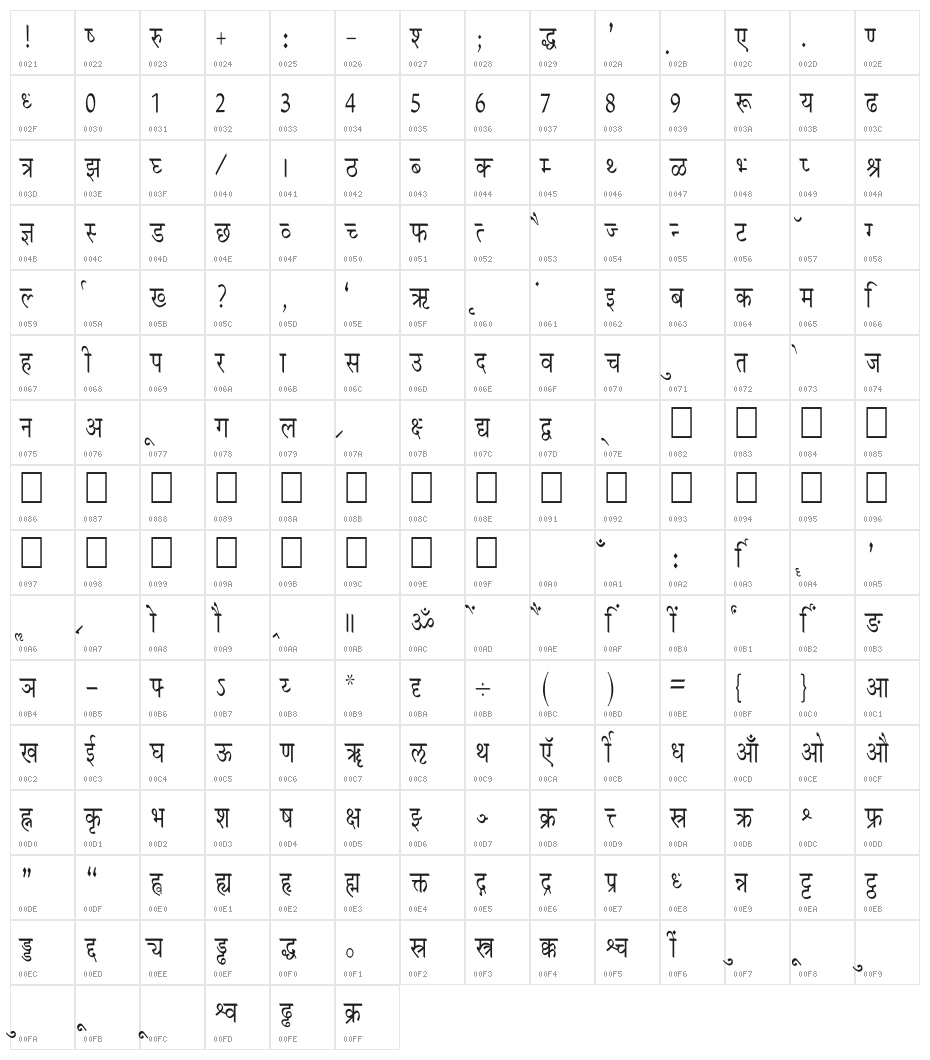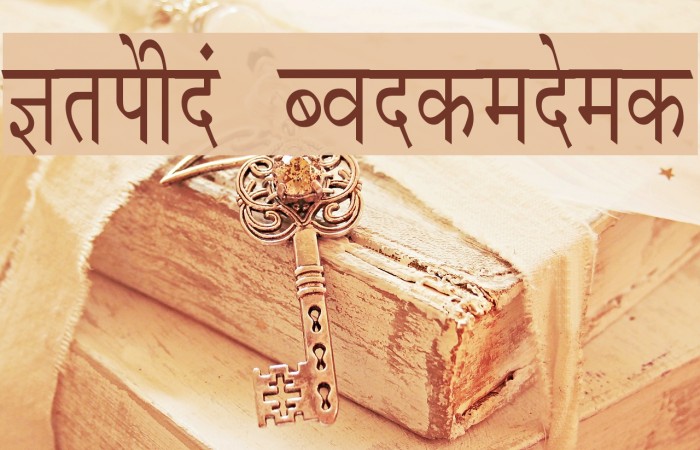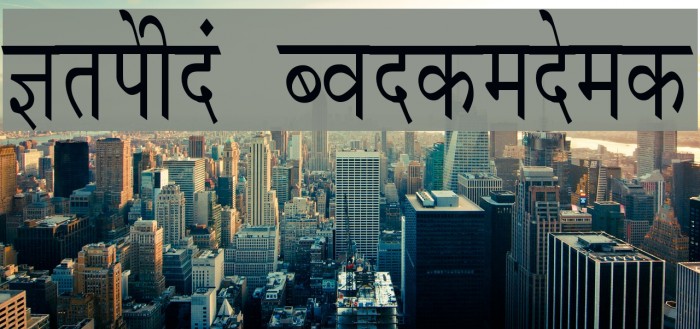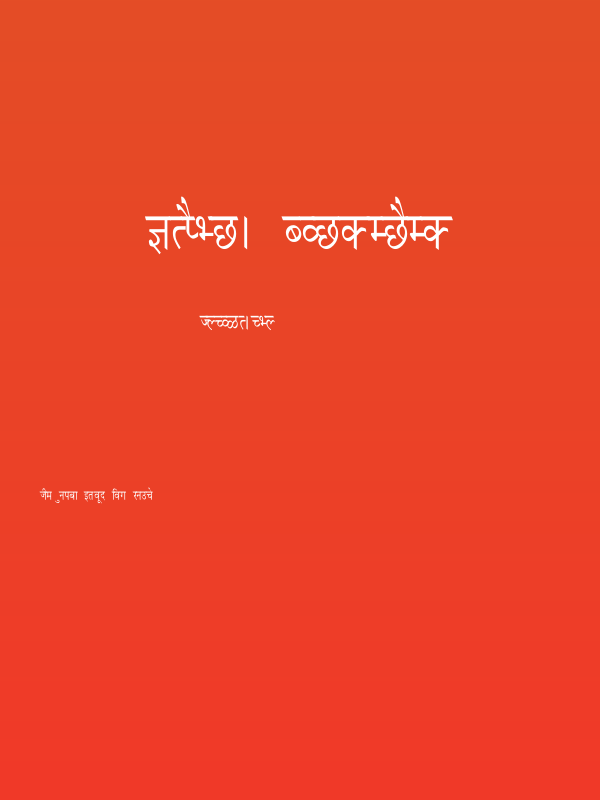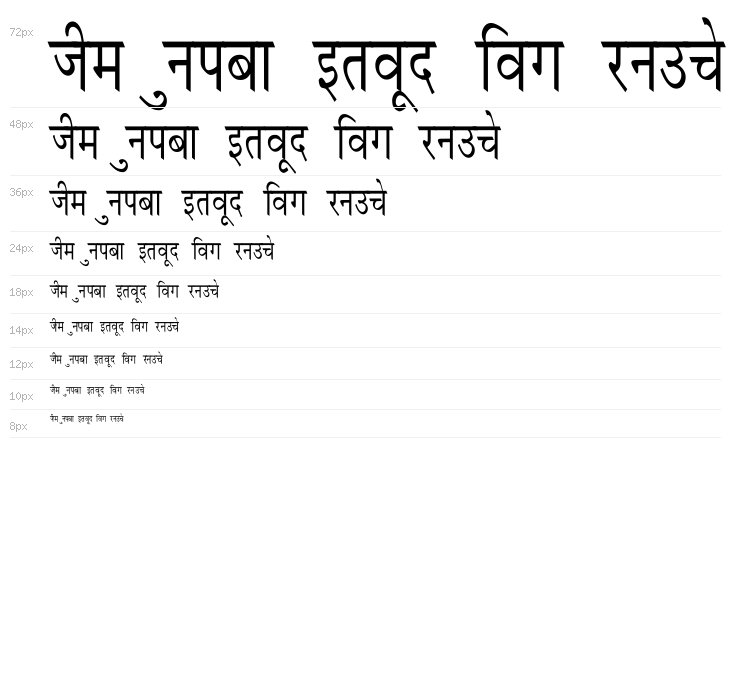
Krishna Condensed Font
| Caso d'uso | Headlines, Posters, Digital Media |
| Progetti proposti | Ideal for headlines, posters, and any design requiring a compact and modern typeface. |